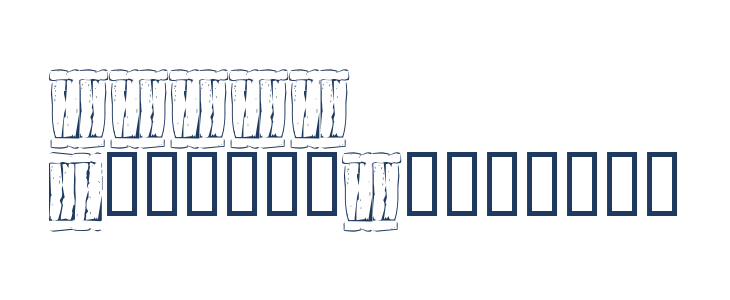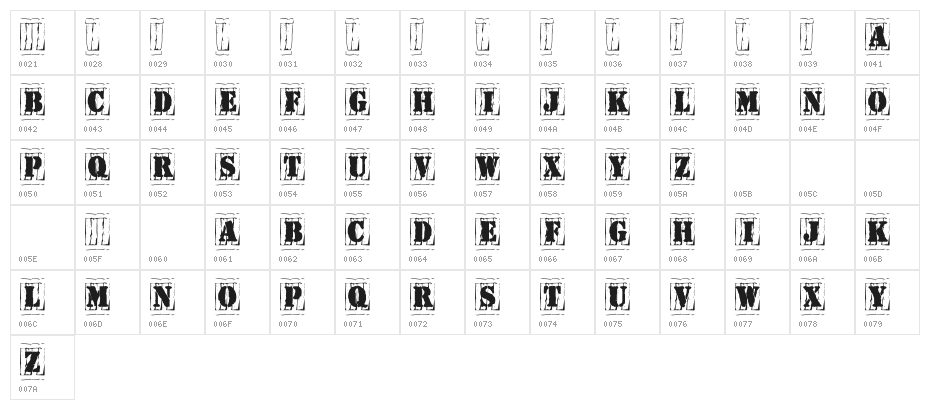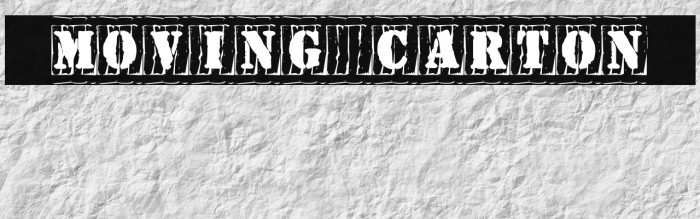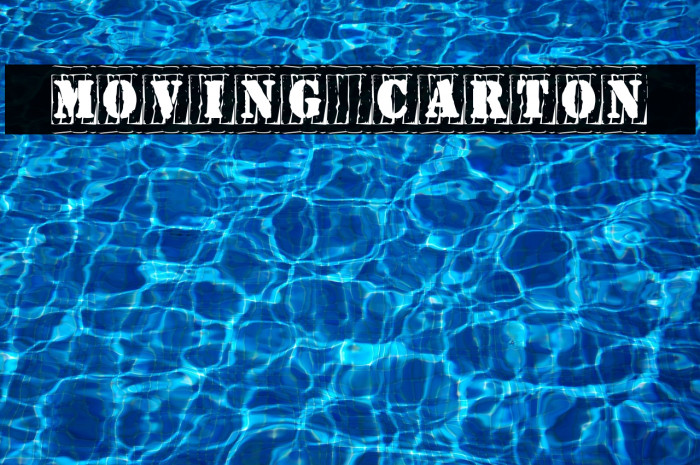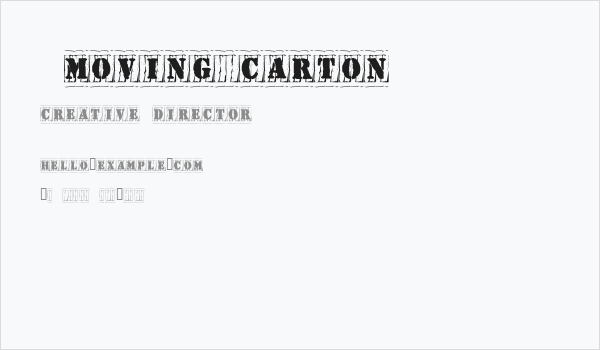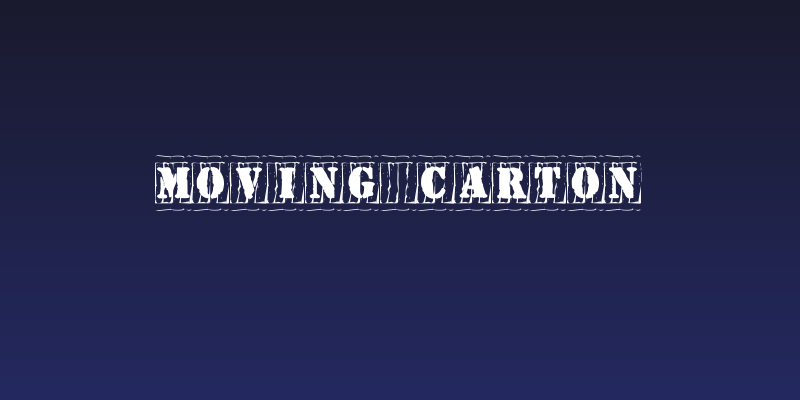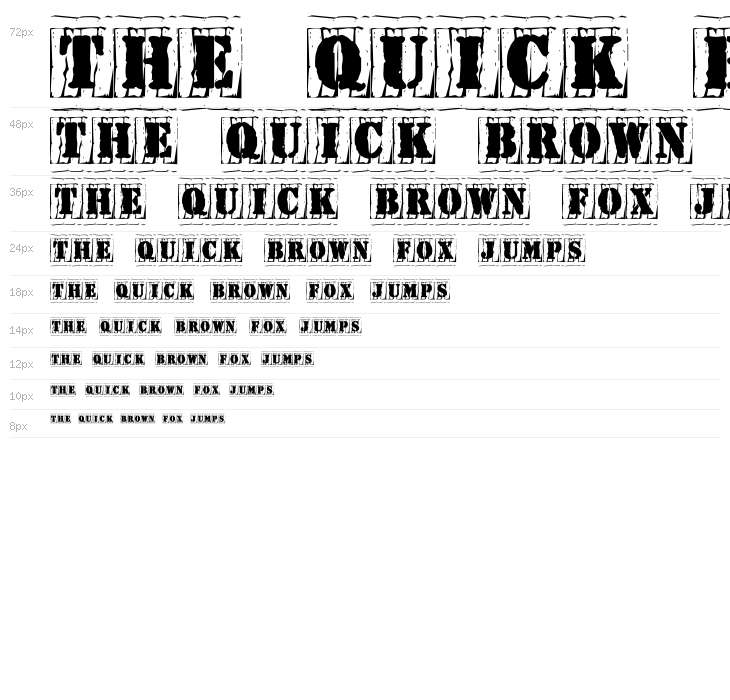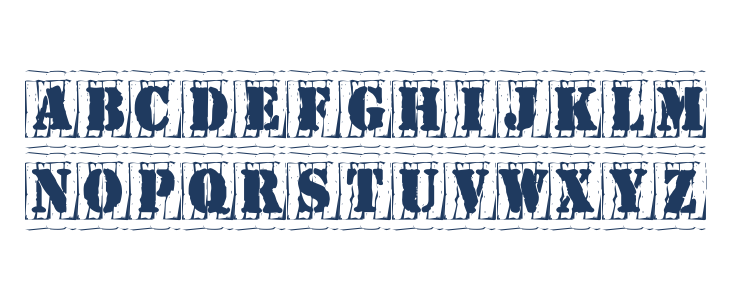
[Moving_Carton] Font
| Progetti proposti | Ideal for packaging design, vintage-themed posters, branding for artisanal products, or any project needing a rustic, handcrafted look. |